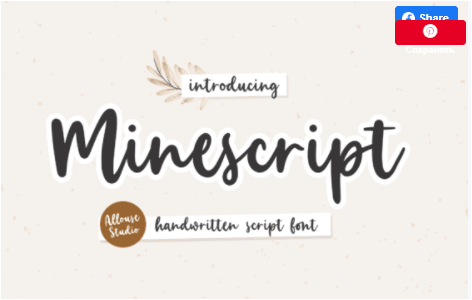
Minescript Font
Minescript — это изящный рукописный шрифт в винтажном стиле.
Он идеально подходит для упаковки продукта, брендинга, обложки журнала, социальных сетей, свадьбы или просто для выражения слов над фоном.
Minescript — это изящный рукописный шрифт в винтажном стиле.
Он идеально подходит для упаковки продукта, брендинга, обложки журнала, социальных сетей, свадьбы или просто для выражения слов над фоном.